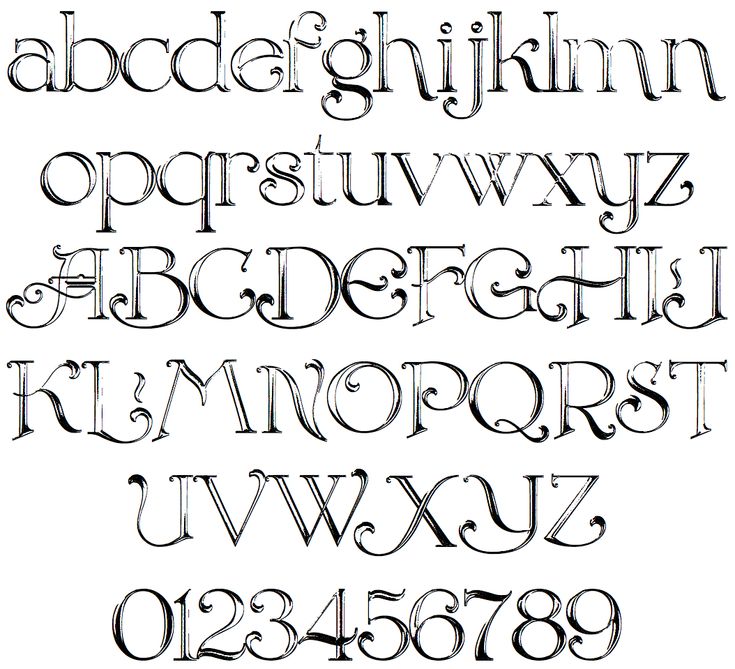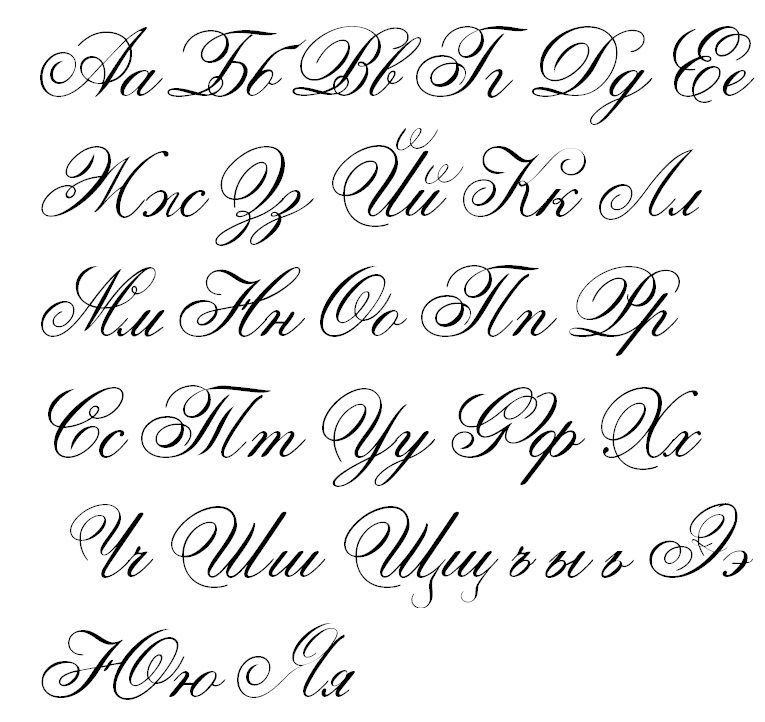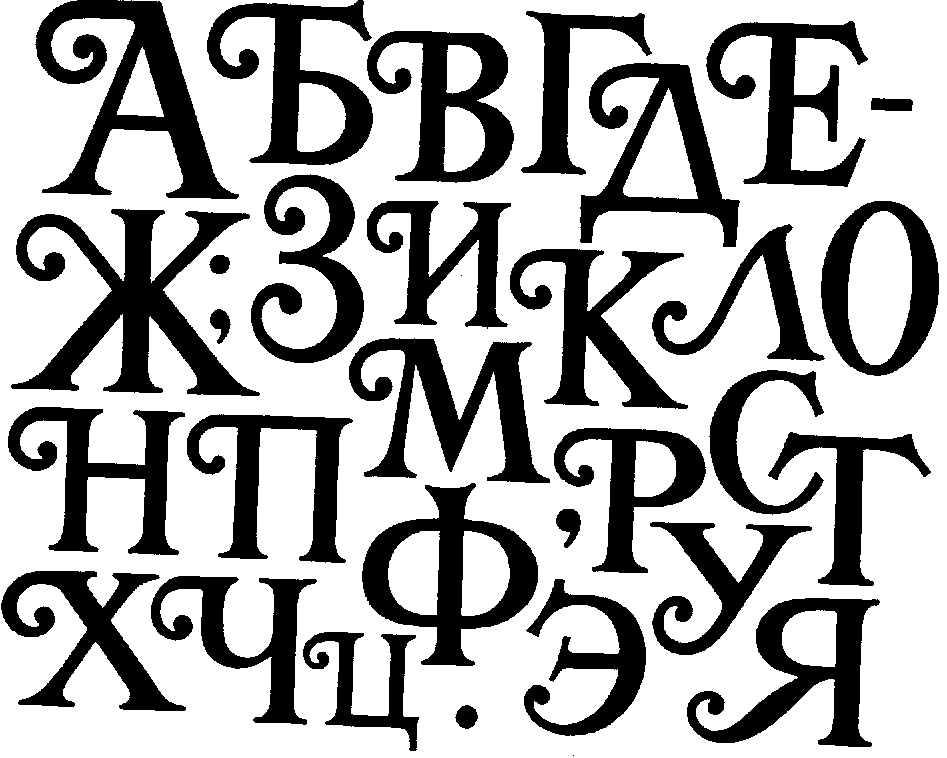
Основные виды шрифтов с примерами
Выбор правильного шрифта для дизайна — это одновременно искусство и наука. Конечно, вы хотите выбрать шрифт, который эстетичен и соответствует настроению вашего проекта, но он также должен быть подходящим и удобочитаемым для сопроводительного текста. Благодаря бесконечному количеству вариантов, доступных в Интернете, выбор идеального шрифта может оказаться непосильной задачей для любого дизайнера.
Самый простой способ определить правильный шрифт — разбить его на категории. Существует пять основных видов шрифтов, каждый из которых обладает уникальными качествами, которые делают его подходящим для различных случаев. Давайте рассмотрим каждый из основных видов шрифтов по отдельности.
Виды шрифтов
Шрифты с засечками (Serif)
Пример брендов, использующих засечки: Zara, Tiffany & Co
Это самые старые типы шрифтов, первые образцы которых появились еще в конце 15 века.
Слово «засечки» относится к маленьким ножкам, расположенным вверху и внизу каждой буквы. Эти крошечные завитки созданы кистями художников и добавлены к буквам в качестве декоративных элементов.
Шрифты с засечками можно разделить на несколько подкатегорий (Старый стиль, Классический, Неоклассический, Переходный и так далее). Сегодня шрифты с засечками являются одними из самых популярных используемых гарнитур, а такие стили, как Times New Roman, всегда присутствуют в книгах, документах и даже в некоторых логотипах.
Этот вид шрифта отличается более консервативным дизайном и (несмотря на некоторые из множества подклассов) наличием засечек вверху и внизу большинства букв.
Психология шрифтов с засечками: шрифты с засечками популярны среди компаний, которые стремятся изобразить элегантный, утонченный бренд. Логотипы с этими типами демонстрируют атмосферу традиций, респектабельности и надежности.
Кроме того, засечки помогают компаниям выглядеть более устоявшимися и идеально подходят для обозначения идентичности, основанной на авторитете и величии.
Организации в академической, редакционной и финансовой областях отдают предпочтение шрифтам с засечками благодаря их консервативному и респектабельному внешнему виду.
Шрифты без засечек (Sans Serif)
Пример брендов, использующих шрифты без засечек: LinkedIn, Calvin Klein
Шрифты без засечек обходятся без изюминок своих предшественников в пользу более чистого и современного подхода, и этот контраст позволяет им хорошо сочетаться со шрифтами с засечками. Они датируются 19 веком и стали чрезвычайно популярны в 20-30-х годах прошлого столетия. В середине 20-го века немецкие дизайнеры создали один из наиболее популярных шрифтов, относящихся к типу шрифтов без засечек — Helvetica.
Эти шрифты отличаются чистыми прямыми линиями. Они подчеркивают удобочитаемость и простоту для большей масштабируемости. Шрифты без засечек также можно разделить на несколько подкатегорий, включая стили гротеск, геометрический и гуманистический.
Психология шрифтов без засечек: эти типы шрифтов предлагают чистый, серьезный вид.
В них подчеркивается ясность и дальновидность, но они также могут быть смелыми и привлекательными благодаря отточенному и эффективному дизайну. Компании, которые выбирают это семейство шрифтов, ставят во главу угла чувствительность и честность.
Шрифты Slab Serif
Пример брендов, использующих Slab serif: Honda и Volvo
Slab serif — это вариант традиционной типографики с засечками, появившейся в 19 веке. Эти шрифты выделены жирным шрифтом и подчеркивают отличие от своих классических аналогов. Ножки, определяющие шрифты с засечками, больше и похожи на блоки (читай: выглядят как «плиты»).
Эти типы шрифтов отличаются солидным, смелым подходом и больше подходят для современных брендов, чем для классических. Эти шрифты могут быть округлыми или угловатыми, некоторые из них очень напоминают стили пишущей машинки.
Психология шрифтов Slab serif: все эти шрифты передают чувство уверенности, надежности и творческого мышления благодаря своим жирным линия.
Бренды, пытающиеся произвести большой фурор или показать, насколько инновационны их идеи и продукты, выбирают типы шрифтов с засечками, поскольку они могут помочь передать чувство важности и потребности.
Рукописные шрифты (Script)
Пример брендов, использующих рукописные шрифты: Кока Кола и Cadillac
Рукописный вид шрифтов приобрел популярность в 20-м веке. Эти типы шрифтов обходятся без блочной печати в пользу более естественного стиля курсива.
Рукописные шрифты определяются их завитушками и завитками, которые называются «росчерками». Как правило, рекомендуется использовать эти шрифты экономно, так как они могут повлиять на удобочитаемость и затруднить понимание и масштабирование словесных или буквенных знаков.
Психология рукописных шрифтов: как правило, скриптовые шрифты вызывают идеи элегантности, творчества, свободы и женственности. Их изогнутые и пышные стили также демонстрируют более практичный и индивидуальный подход к бизнесу.